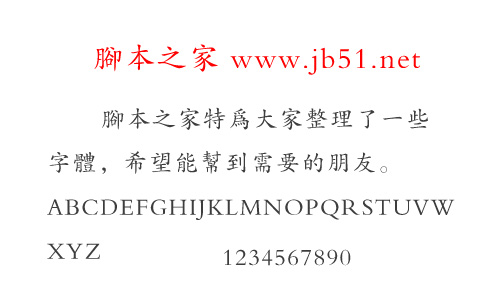
方正中楷繁體字體是方正字體庫中的一種字體,方正中楷的風(fēng)格與方正楷體一致,且采用臺灣筆形,只有繁體字庫。這款字體字形端正嚴(yán)謹(jǐn),筆畫平直,布白均勻,適用于各類報(bào)紙、雜志和書籍中的正文。方正中楷的BIG5封裝版本是專門針對港臺用字的。使用GB12345-90封裝的版本要留意文本校對。喜歡的朋友們可以前來下載使用。